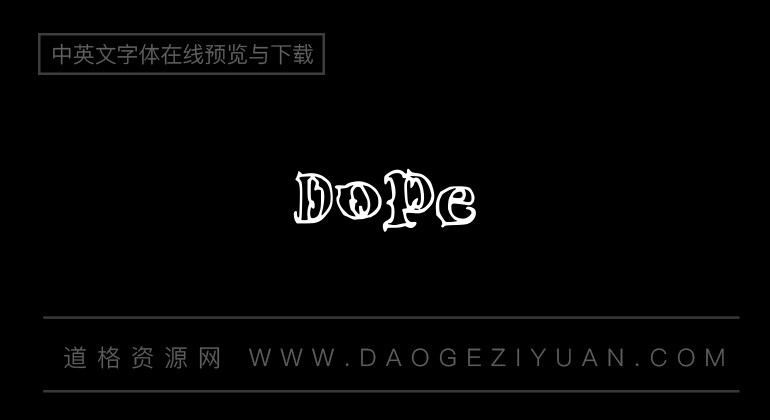
Dope字体是一种比较新的字体,它被设计用来提供一种有趣的、独特的、现代的风格。它的设计灵感来自于欧洲和美国的潮流文化,具有流行、叛逆和复古的特色,可以用于广告、标识、标题、封面等等。它的字体特点是利用细节和自然的设计,使字体看起来更有活力,而且还有多种字体可以选择,可以满足不同的设计需求。内容介绍
Dope是一款非常不错的手写艺术字体,具有很好的视觉感,适合于文化类的宣传设计、商业类品牌的广告和产品包装设计以及个性化文字排版等较多场景。